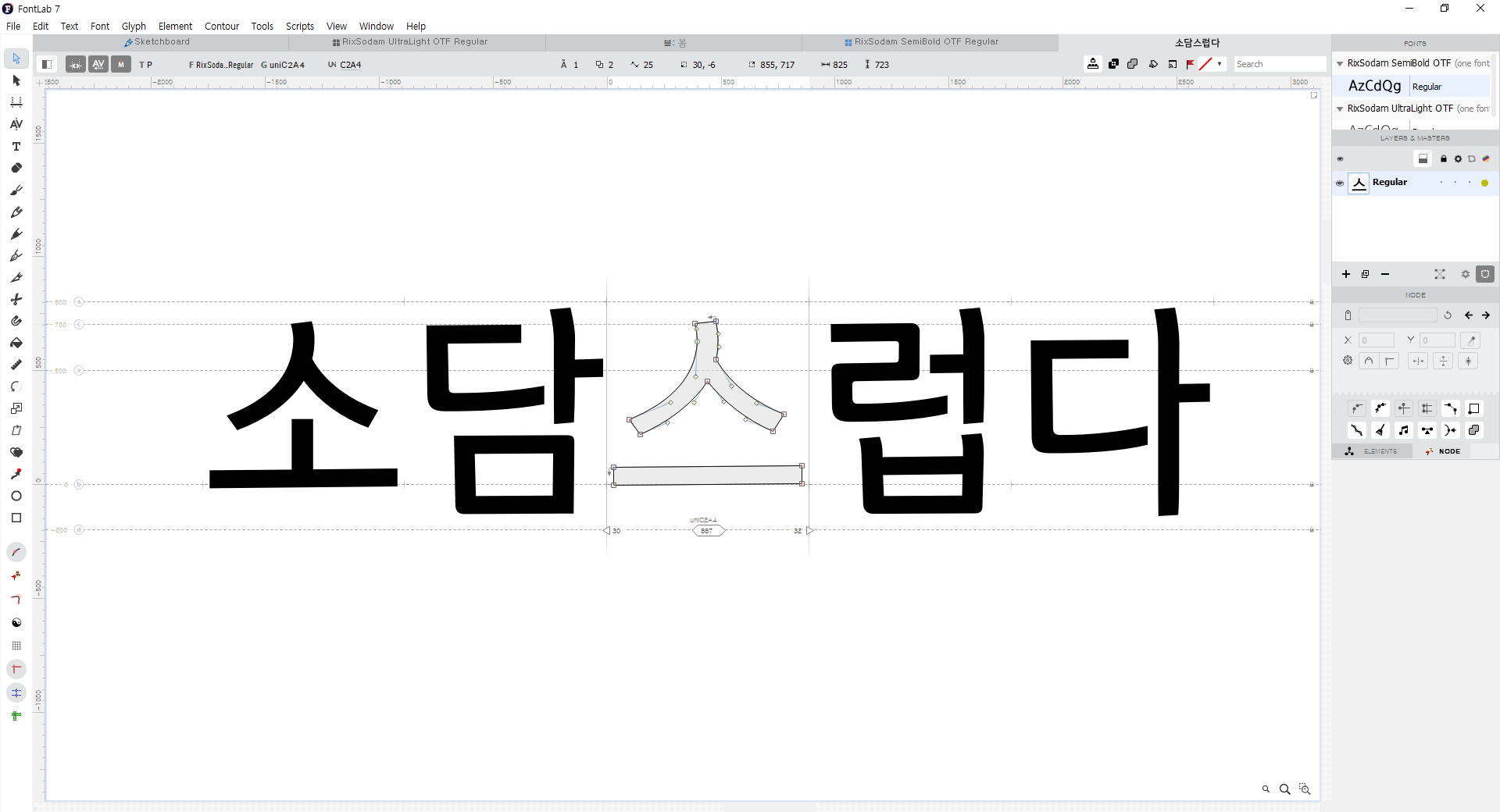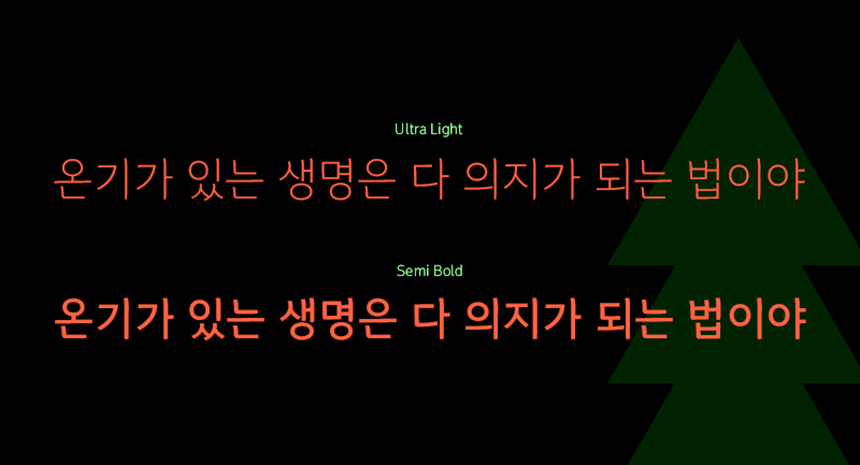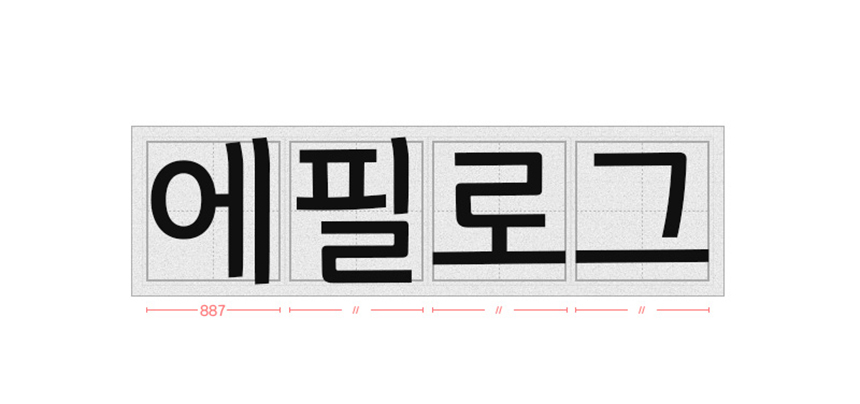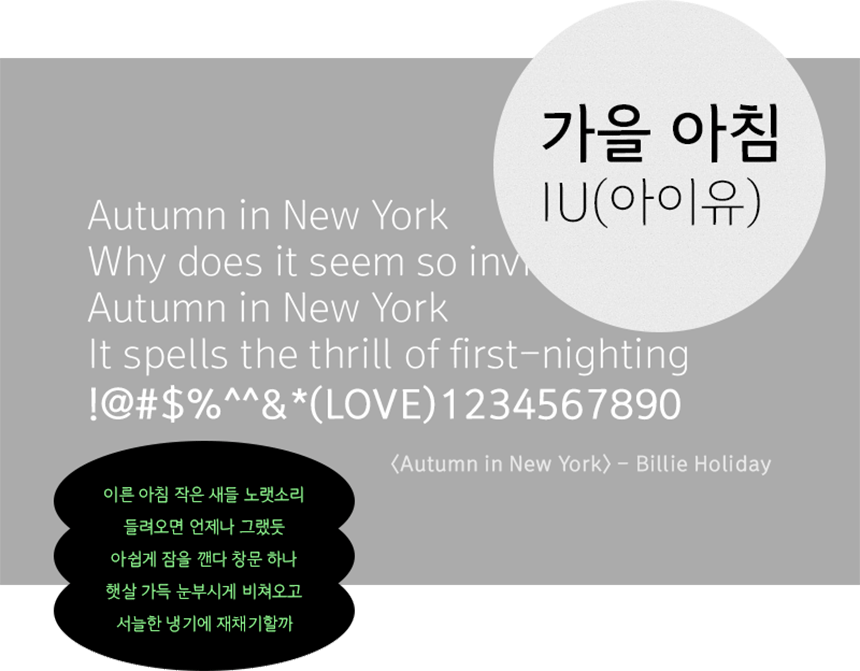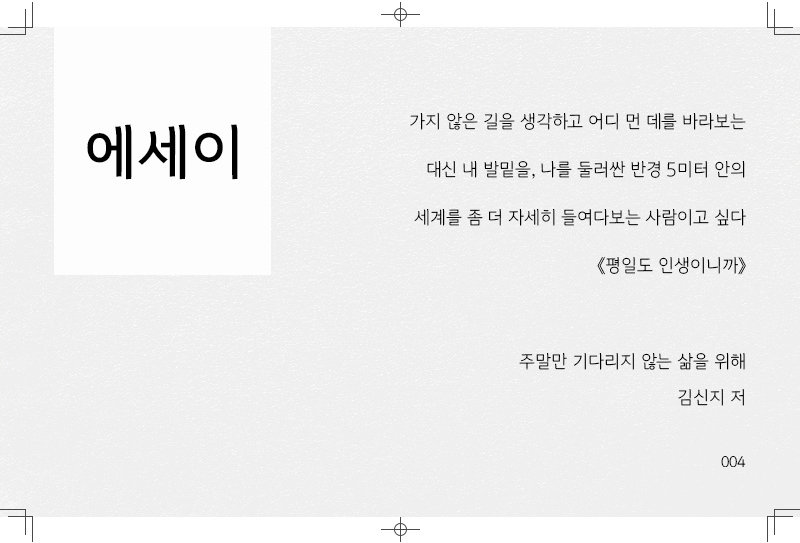
안녕하세요. 바람이 서늘하게 느껴지는 가을과 겨울 사이, 찬 공기가 점점 익숙해지는 계절입니다. 이렇게 추워지는 날씨에 따스함을 줄 수 있는 11월의 신규 폰트,「Rix소담체」를 소개합니다! 본문과 제목 모두 활용이 가능하도록 두 가지 굵기로 제작된 깔끔하고 담백한 느낌의 서체인데요. 'Rix소담체' 제작에 참여한 이지윤 디자이너와의 인터뷰를 담아봤습니다:)
11월의 신서체를 맡아주셨는데요. 어떻게 기획하게 되셨는지, 폰트명을 ‘소담체’로 지은 이유 등 설명 부탁드려요!
먼저 Rix소담체는 따뜻하면서도 담담한 매력을 가진 폰트예요. 시선을 강하게 사로잡는 특징은 없지만 손글씨의 특징인 꺾임과 곡선이 자연스럽게 어우러져있어요. ‘모자라지도, 넘치지도 않고 깔끔하다’라는 뜻을 가지고 있는 단어 ‘소담스럽다’가 이 폰트와 너무 잘 어울리더라고요. ‘Rix소담’이라고 불려도 되지만 아날로그틱한 느낌을 더해주고자 ‘체’를 붙여 최종적으로 Rix소담체가 되었습니다.
이 폰트는 이래서 특별하다!라는 포인트가 있다면?
Rix소담체의 가장 큰 매력은 아무래도 폰트 자체에서 느껴지는 감성이라고 생각해요. 얇은 획과 꺾임, 그리고 굴림이 만나면서 만들어내는 감성이요! Semi Bold를 작업하며 느낌을 해치지 않기 위해 노력했습니다.
Rix소담체, 어디에 어떻게 쓰면 좋을까요?
소담체는 아무래도 감성적인 글에 찰떡일 것 같아요. 손편지 느낌의 이미지나 소설, 시, 에세이 등 감성 가득한 글을 담은 책 표지, 본문에도 잘 어울릴 것 같습니다!
소담스럽다 : 깔끔하여 보기 좋은 데가 있다
'소담스럽다'라는 말이 참 잘 어울리는 소담체는 본문에 주로 쓰는 얇은 굵기 Ultra Light로 처음 제작되었어요. 굵은 두께 Semi Bold를 추가로 파생하여 소담체의 깔끔 담백한 맛을 제목에도 활용할 수 있어요.
소담스럽다
1. 모자라지도 넘치지도 않고 깔끔하여 먹음직하고 보기 좋은 데가 있다
2. 알차고 보기에 좋은 데가 있다.
고딕 형태지만 손글씨의 특징인 꺾임과 곡선이 자연스럽게 조화를 이루어 전체적으로 따뜻하고 감성적인 느낌이 들도록 제작했습니다. 손으로 쓴 듯 살짝 꺾어 들어오는 곡선이 직선적인 획과 만나 소담체만의 특유의 감성을 보여줍니다.
편안하고 담백한 손글씨
Rix소담체는 887의 적당한 고정폭을 가지고 있어 편안하고 안정적인 느낌을 줍니다. 적절하고 일정한 간격으로 깔끔한 이미지를 더욱 돋보이게 해 줍니다. 손글씨 느낌이 들어간 서체에서 흔히 볼 수 없는 고정폭 글꼴로 장문의 텍스트에서도 정돈된 느낌이 들도록 설계한 부분이에요!
따듯함을 품은 가을 아침
영문, 숫자, 약물 또한 한글의 디자인을 그대로 차용하여 함께 사용했을 때 조화롭고 자연스럽게 어우러지도록 제작했습니다. 편안하면서도 따스한 감성이 느껴지는 서체의 분위기가 선선한 가을과 참 잘 어울리는 서체인 것 같아요🍁🍂
| 이렇게 활용해 보세요
위에 인터뷰에서 디자이너님이 말씀하셨듯, Rix소담체로 손편지, 시, 에세이 등의 글을 적어보면 잘 맞은 옷을 입은 듯 편안해 보입니다. 감성 가득한 글을 담은 책 표지, 본문 등에도 활용해 보세요.
디바이스 환경에서도 깔끔하고 담백한 느낌이 돋보여 짧은 노트나 메모 등 어플에서 사용하기에 좋아요. 차분한 감성의 인쇄물이나 배너, 광고 문구에 활용하기에도 좋습니다.
오늘 소개해드린 Rix소담체는 기존에 제작하던 크고 굵직한 폰트들과 다르게 편안하고 담담한 느낌을 주는 서체인데요. 이런 서체들은 자주 나오지 않기 때문에 더 메리트가 있고 신선하게 다가갈 수 있을 것 같아요:) 조금씩 차가워지는 바람에 몸이 움추러드는 계절, 소소한 따듯함을 주는 서체가 되었으면!